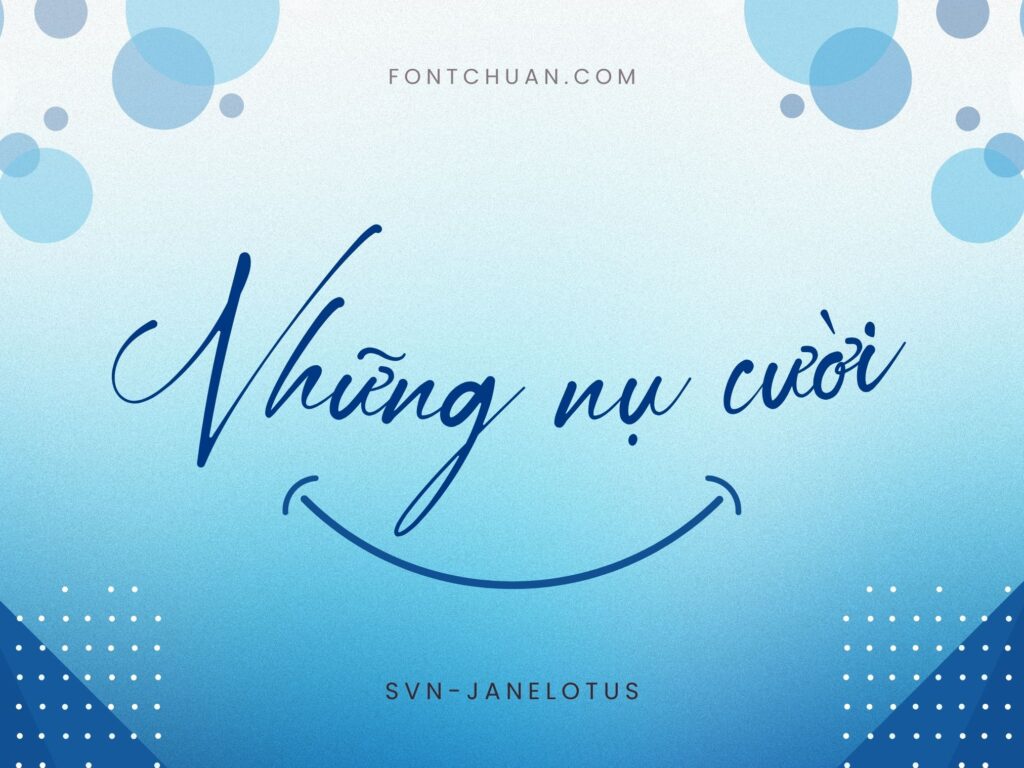
Font SVN Janelotus Việt Hóa
Font SVN Janelotus là phiên bản Việt hóa của kiểu chữ Janelotus, được thực hiện bởi STYLEno.1 Fonts. Janelotus là một font chữ ký và cũng là một Font chữ viết tay hoàn hảo với nét chữ tự nhiên và phong cách thanh lịch, phù hợp cho nhiều dự án như logo, thương hiệu, thiệp mời, thiết kế văn phòng phẩm, thiết kế đám cưới, bài đăng trên mạng xã hội, quảng cáo, bao bì sản phẩm, thiết kế sản phẩm, nhãn mác, nhiếp ảnh, watermark và các sự kiện đặc biệt khác. Font này bao gồm các ký tự chữ hoa, chữ thường, chữ số và dấu câu, hỗ trợ đa ngôn ngữ. Với thiết kế tinh tế và mềm mại, Janelotus mang đến vẻ đẹp sang trọng và chuyên nghiệp cho các dự án thiết kế.
SVN Janelotus lý tưởng cho các dự án thiết kế yêu cầu sự thanh lịch và chuyên nghiệp, như thiết kế logo thương hiệu, thiệp mời đám cưới, tiêu đề tạp chí và các ấn phẩm truyền thông. Các ngành nghề như thiệp cưới, giáo dục và quảng cáo có thể tận dụng font này để tạo điểm nhấn trong thiết kế. Ngoài ra, font cũng thích hợp cho các sự kiện như Valentine, Sinh nhật, Tết và các lễ hội khác.